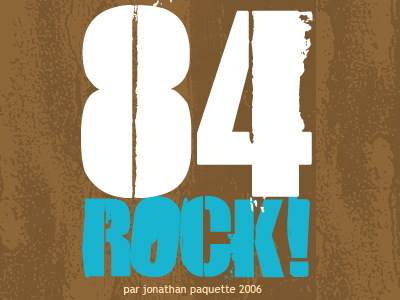
84 Rock! von Charles S. und Jonathan Paquette ist eine kostenlose, im Grunge-Stil gehaltene Display-Schrift, die an Rock-Poster erinnert. Sie besticht durch ihre wuchtige Silhouette und raue, vertikale Kratzer, die sich durch die Buchstaben ziehen. Die Formen wirken kompakt und laut; quadratische Rundungen und abgenutzte Kanten verleihen der Schrift eher die Optik eines gealterten Konzertbanners als eines glatten Retro-Designs.
Sie eignet sich perfekt für Musik-Flyer, Club-Poster, Album-Cover, Event-Branding, Merchandise und kurze Titel, bei denen es auf Charakter statt Perfektion ankommt. Setzen Sie sie für große Schriftzüge, Cover-Lines oder kompakte Überschriften ein – die massiven Buchstaben und die kratzige Textur sorgen sofort für Aufmerksamkeit.